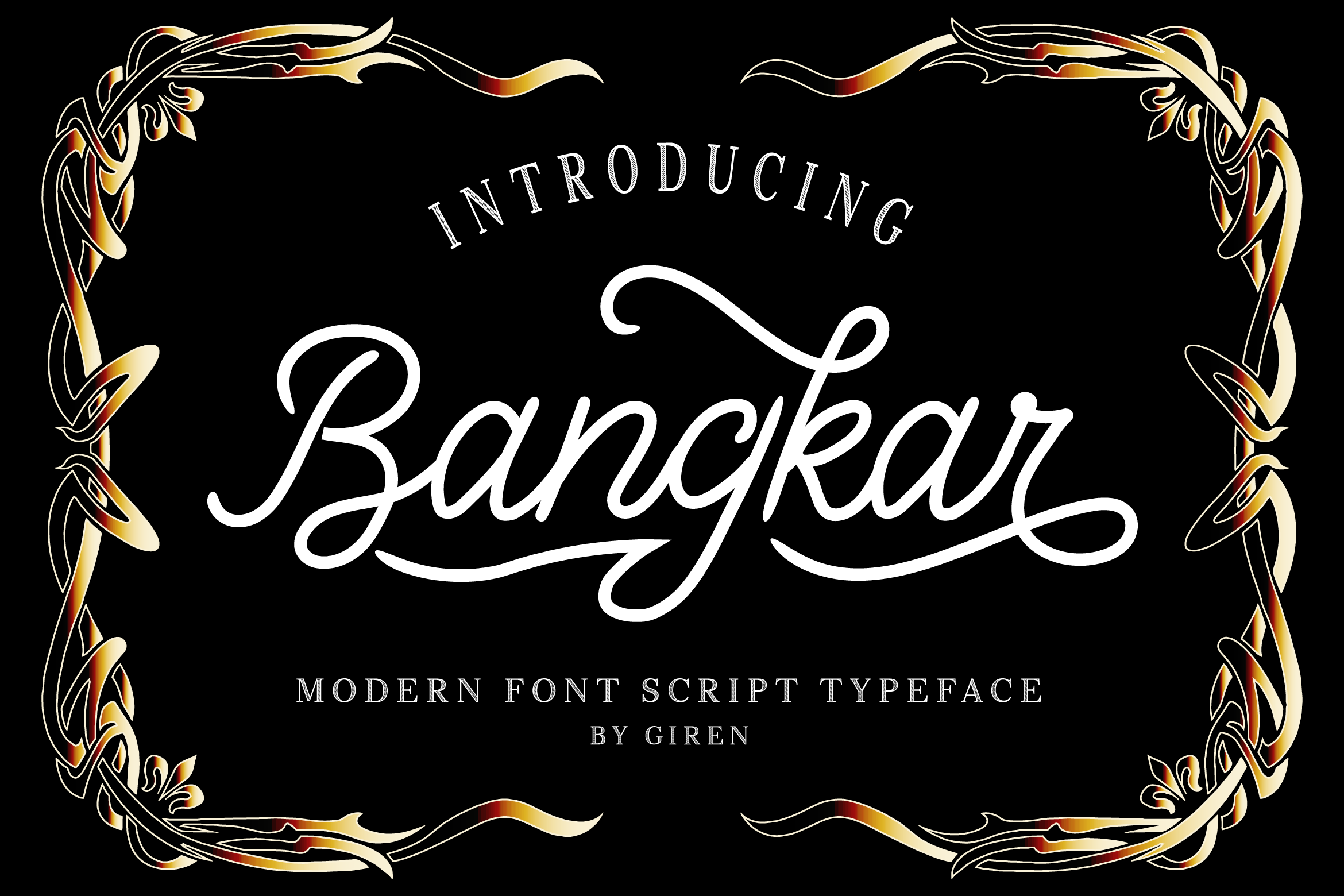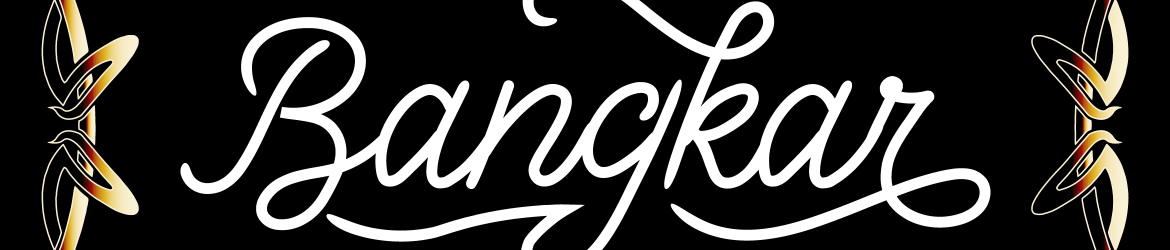
Aqui está uma versão em português do Brasil para a página de download da fonte ‘Bangkar Script Font’, seguindo as instruções fornecidas: Um novo talento chega ao mercado das fuentes digitais, e nós estamos felizes por ter esse inédito na nossa coleção. Chamamos-lhe Bangkar Script, uma fonte que carrega um toque natural e elegante, perfeitamente adaptada para uso em diferentes formatos de mídia. Este design handwritten foi criado com o objetivo de ser versátil, adequando-se a diversos usos: desde criação de logotipos e gráficos para roupas, até design de carteirinhas devidos ou marcas de impressão. Seja para editoração de publicações impressas ou online, assinaturas digitais ou materiais impressos à mão, Bangkar Script é a fonte perfeita para qualquer projeto. Com sua simplicidade e profundidade única, o Bangkar Script oferece uma solução completa que combina beleza com facilidade na escrita. Ideal tanto para aqueles que desejam adicionar um toque autêntico em seus trabalhos quanto para os profissionais buscando uma fonte confiável e de qualidade. Engane-se se acha que Bangkar é apenas mais uma fonte; ele carrega consigo o poder de transformar sua arte digital num marco definitivo. Se você está procurando por um novo amigo na sua coleção de fuentes, então o Bangkar Script é certamente aquele em quem deve apostar. Ele traz um toque natural que se torna uma escolha inegável para qualquer projeto onde a essência e a personalidade do design são primordiais.